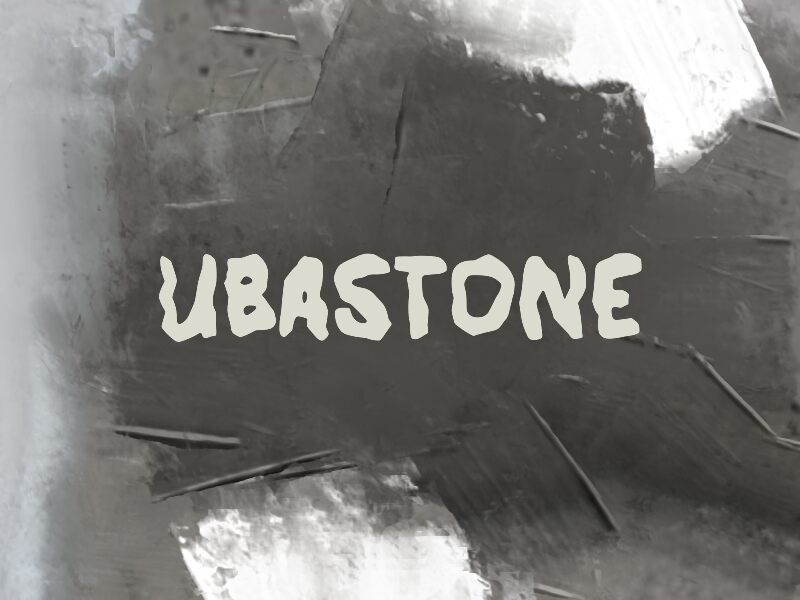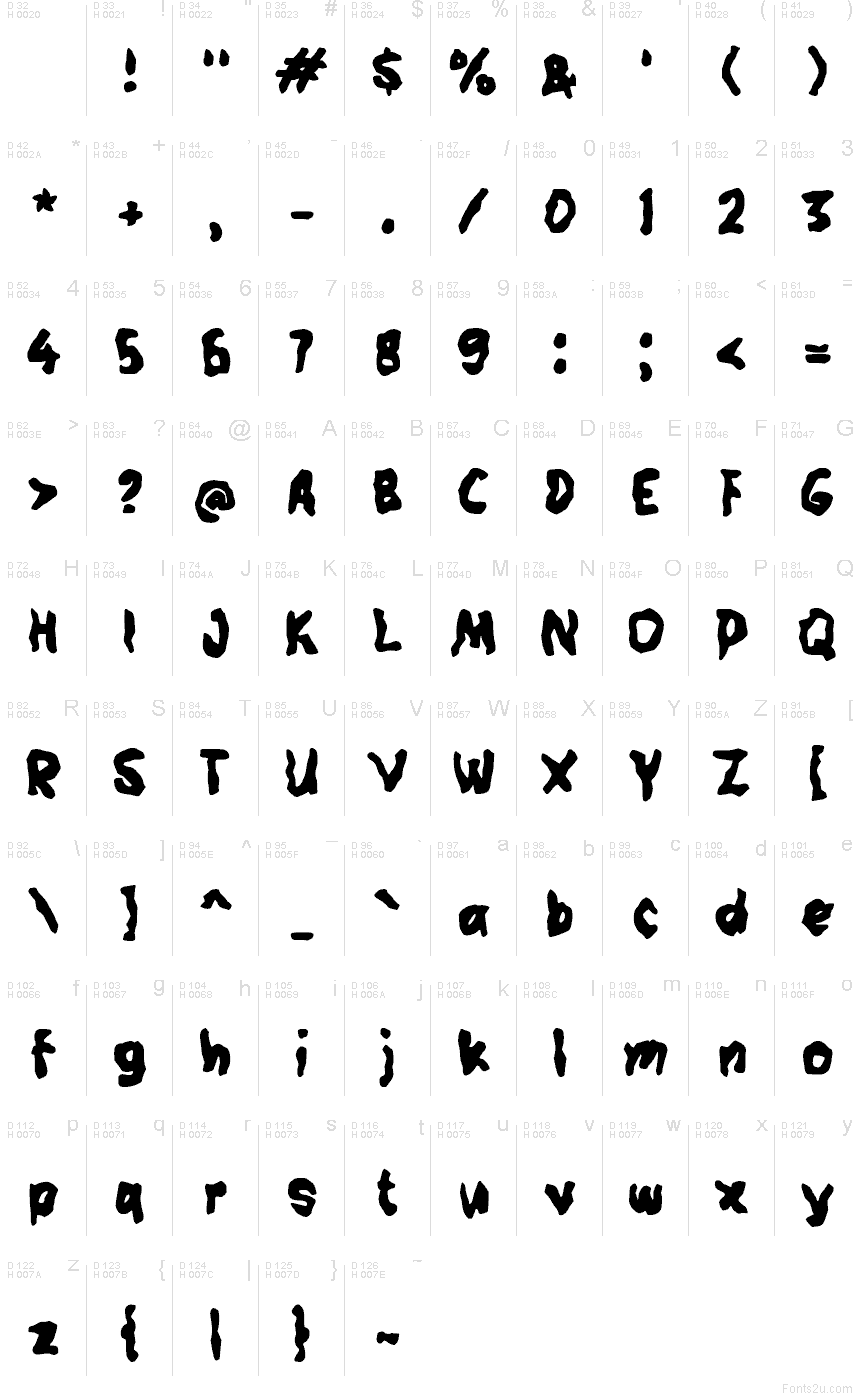
Ubastone di Wep è un font display gratuito e distorto, con un look cartoon grezzo, quasi come se fosse scolpito nella pietra. Le lettere appaiono gonfie, sbilenche e lavorate a mano, con silhouette massicce, bordi tremolanti e aperture scavate che conferiscono al font un carattere ruvido, giocoso e leggermente preistorico.
È perfetto per titoli di poster, loghi di giochi, copertine di zine, volantini per feste a tema e brevi titoli dove un font gratuito deve puntare più su una silhouette d'impatto che sulla precisione. Dato che le maiuscole sono così irregolari e corpose, UBASTONE è ideale per parole brevi, badge e marchi in stile monogramma, dove la sua texture frastagliata e compressa può davvero parlare da sola.
Ubastone